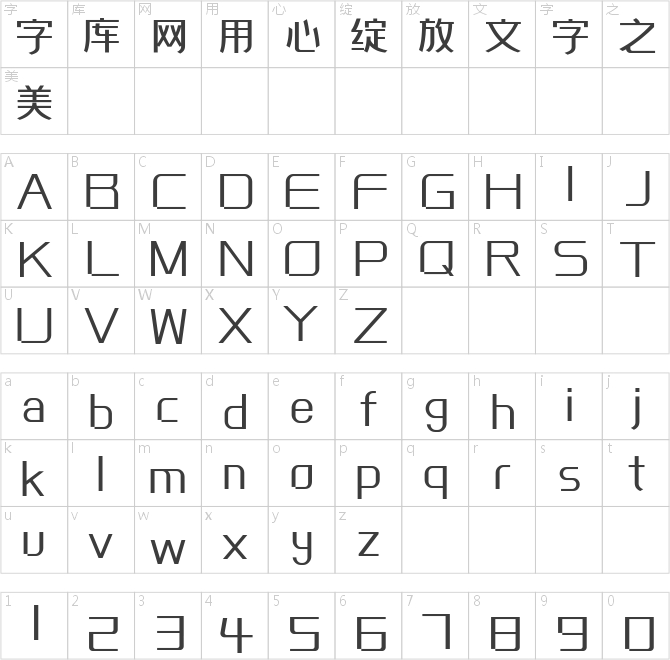
字体名称: 卓健橄榄简体
卓健橄榄简体
卓健橄榄简体介绍
卓健橄榄简体是由卓健设计团队制作,是一款相对较时尚的字体,部分笔画的斜切处理,也让字体更具设计感和时尚属性,整体中心是偏上一点,更符合现代审美。字体圆角设计,让整个字体更加圆润,富亲和力。口字结构,左下角留白,个性化处理更具特色。字库共7050个常用字,感谢卓健设计团队的分享。
卓健橄榄简体字体字库是一款让人赏心悦目、百看不厌的中文字体,适合各类广告和产品包装设计应用,字体大小3.66MB,格式为ttf字体,上传用户是Bot,作者/版权方为卓米品牌设计